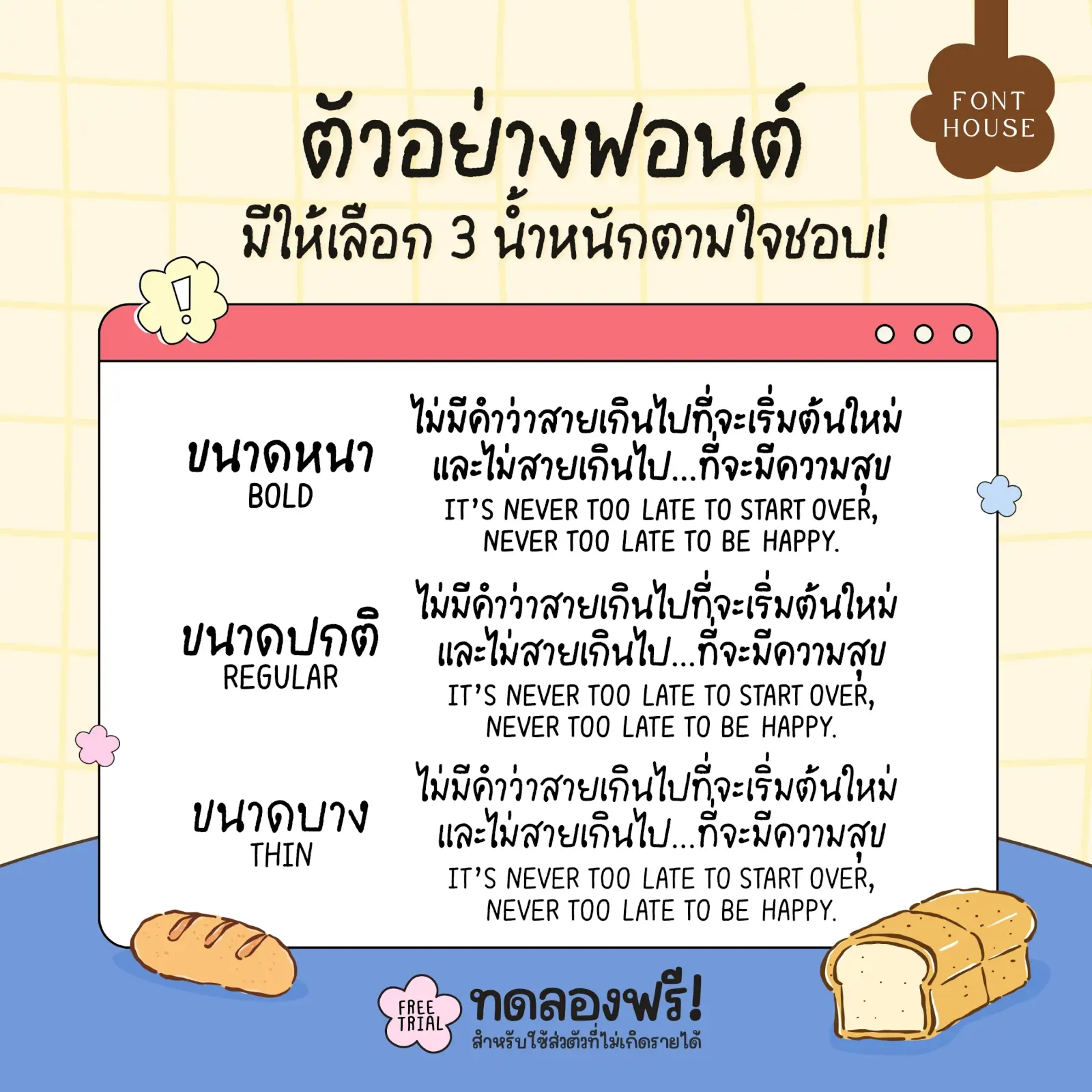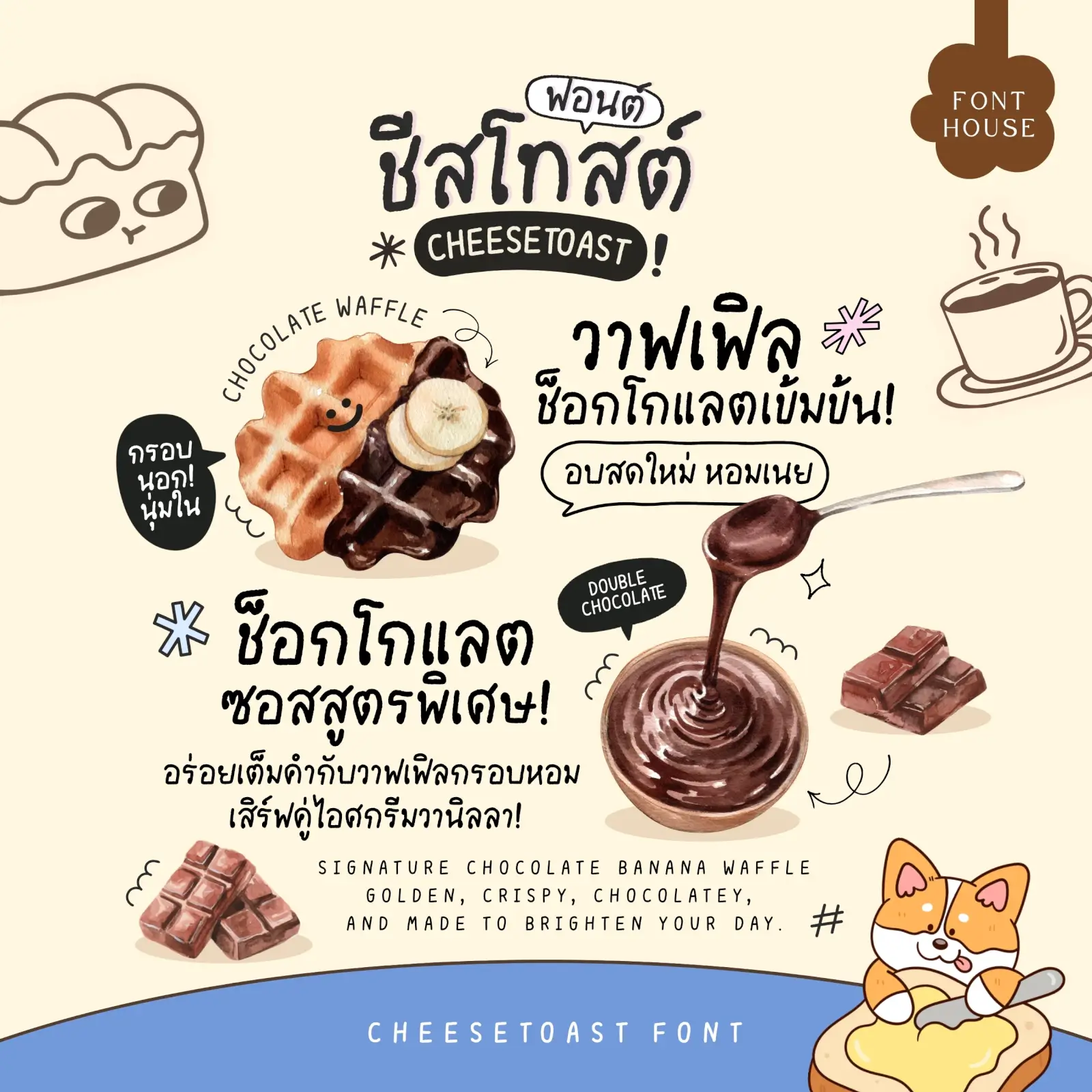
ฟอนต์ชีสโทสต์ (FH Cheese Toast) – ฟอนต์ลายมือสไตล์มินิมัล ตัวอักษรมีเท็กซ์เจอร์ มีความเก๋ และมีคาแรกเตอร์เหมาะกับงาน
หัวข้อ รายละเอียด หรือซับคลิป รีวิว และคอนเทนต์
- มี 3 น้ำหนัก
ชีสโทสต์ (FH Cheese Toast)